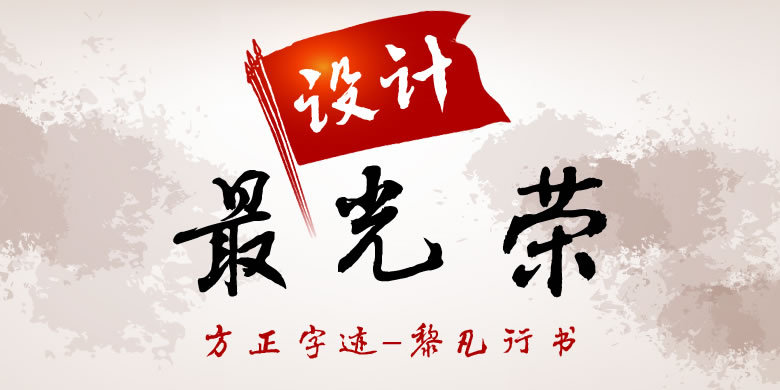
方正字迹-黎凡行书
字体品牌: 方正字迹 设计师:黎凡 字体分类:行楷、行书 字体属性:精品字 字符集:大陆简体(GB2312-80)、大陆繁体(GB12345-90)、简繁扩展(GBK) 发布时间: 2013
方正字迹-黎凡行书偏于行楷,结体稳健,笔画舒展而中宫紧凑。用笔起伏崎侧多变,起止圆浑,笔致滞涩刚健。这款字体的风格雄浑逸荡,苍劲洒脱,适用于文化、商业类品牌的广告和产品包装设计。